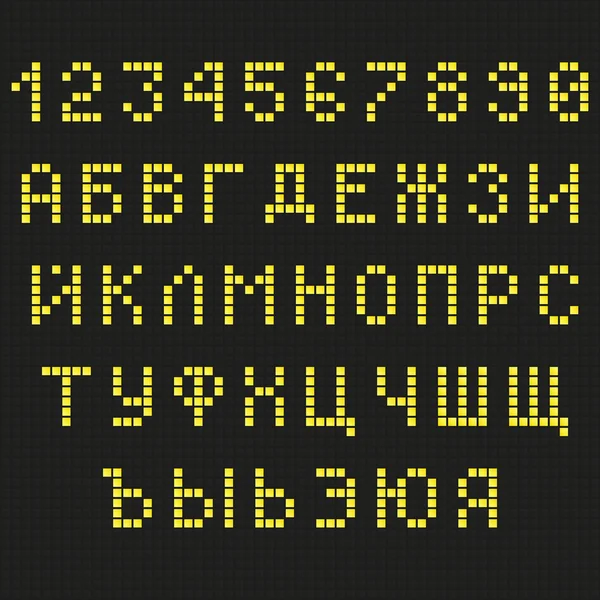
Скажете, это же все электрические приборы? Бесспорно. Но еще у них есть дисплей. Да, холодильники чаще могут обходиться без дисплея, чем смартфоны, но это неточно. В этом вопросе время на стороне холодильников.
В огромном числе современных электронных устройств, как в узкоспециализированных приборах, так и в массовых гаджетах, применяются средства отображения информации, среди которых растровые графические дисплеи занимают доминирующее место. Дисплеи повышают на порядок (часто на несколько) информативность и способствуют созданию более лаконичного, не перегруженного механическими органами управления, корпуса устройства. Также графические дисплеи дают разработчику свободу в создании пользовательского интерфейса: от простого с несколькими строками текста до навороченного с таким количеством текстовой и графической информации, на какое только способна фантазия разработчика.
Монохромная анимацияНапример
монохромная анимацияОднако, графический интерфейс пользователя практически никогда не может быть реализован только графическими примитивами — точками, линиями, геометрическими фигурами — без использования текста.
Текст точно и однозначно «рассказывает» человеку о параметрах системы, ее настройках, прошлом и текущем состояниях.
Сегодня широкое распространение получила пользовательская и специальная электронная техника, значительная часть которой построена на базе микроконтроллеров. Микроконтроллер представляет собой вычислительную платформу, которая может быть запрограммирована почти неограниченным количеством алгоритмов, реализованных на разных языках программирования. Правда, на реализацию накладывают свои ограничения небольшой размер памяти программ (в среднем от единиц килобайт до единиц мегабайт) и ещё меньший размер оперативной памяти, обычно на порядок. А вот драйверы дисплеев, графические библиотеки и сам пользовательский графический интерфейс — отнюдь не компактные алгоритмы. Именно поэтому Вы вряд ли отыщете графические библиотеки для систем на микроконтроллерах, которые бы использовали «взрослые» векторные шрифты для вывода текста. Конечно, есть и такие микроконтроллеры, которые могут дать жару многим серьезным микропроцессорам прошлых лет, но это уже отдельная «весовая категория».
Embedded-шрифт изнутри
Обычно для решения задачи вывода текста в памяти программ создаётся специальный массив данных, так называемая таблица знакогенератора. Не пугайтесь, что он специальный, — все очень просто. В массиве-таблице по сути хранятся растровые изображения всех необходимых приложению символов. Функция графической библиотеки, выводящая текстовые строки, по очереди считывает из таблицы изображение каждого символа и «рисует» его в нужной позиции на дисплее. Все! Идея проста, как столб.
Рассмотрим пример такой таблицы. Предположим, что нам требуется изображение символа шириной 6 и высотой 8 пикселей. Причем, вертикальный ряд пикселей — столбец высотой 8 пикселей — будем кодировать ровно одним байтом. Самый первый байт будет кодировать самый левый столбец. Самый младший бит будет кодировать самый верхний пиксель столбца. Вот пример части такой таблицы:
А вот та же часть в двоичной записи (посмотрите внимательно на биты — каждый из них кодирует один пиксель изображения):
И, конечно же, посмотрим, как эти символы выводятся на дисплее (прямоугольники для лучшего представления знакомест символов):
Такой подход в хранении шрифта имеет свои преимущества и недостатки.
К преимуществам можно отнести небольшой размер таблицы знакогенератора в сравнении с размером файлов стандартных форматов шрифтов для «больших» систем, а также простоту программной реализации графических библиотек, основанных на этом подходе. И первое, и второе чрезвычайно важны в условиях жесткого дефицита памяти и вычислительных возможностей микроконтроллеров.
К недостаткам следует отнести проблемы с масштабированием, что является прямым следствием растровой природы такого шрифта.
Приемлемый по качеству результат получается только, если увеличивать размер символов в кратное количество раз, например, в два, три или четыре раза. В таком случае нет искажений изображений символов, но чем больше кратность увеличения, тем более заметна «растровость» символов. Если в разрабатываемой системе требуется иметь несколько разных шрифтов и масштабирование одного не решает задачу удовлетворительно, тогда используют несколько шрифтов — таблиц знакогенератора.
Предыстория
В своё время мне пришлось разрабатывать программное обеспечение для устройства с графическим дисплеем RDX0120 на контроллере UC1601s. Использовался микроконтроллер Microchip PIC18. Тогда была найдена только одна работающая реализация драйвера, которая была жутко медленной и использовала моноширинный шрифт, внешним видом которого можно разве что отпугнуть будущего пользователя.
И вот, не впечатлившись результатом, была изучена документация на контроллер дисплея и разработана довольно быстрая библиотека.
Шрифт, естественно, было решено сделать заново. Хотелось также, чтобы шрифт был не только моноширинным, но и пропорциональным, то есть чтобы символы в ширину занимали ровно столько места, сколько им требуется, с равным межсимвольным расстоянием.